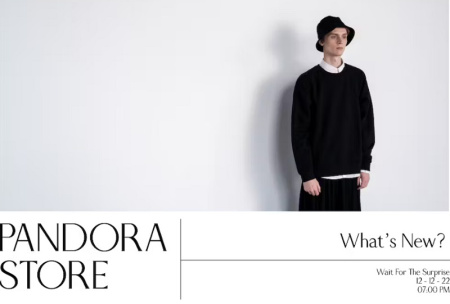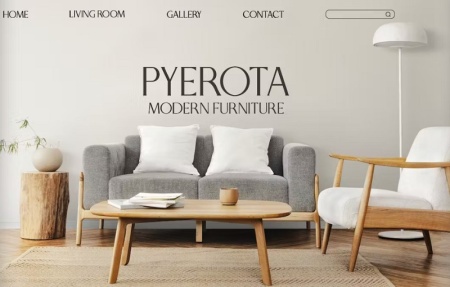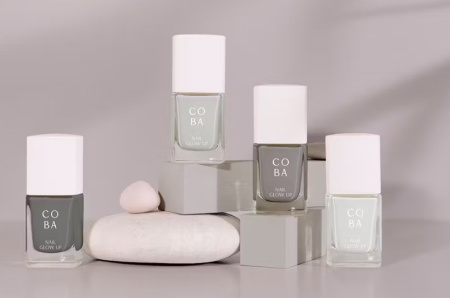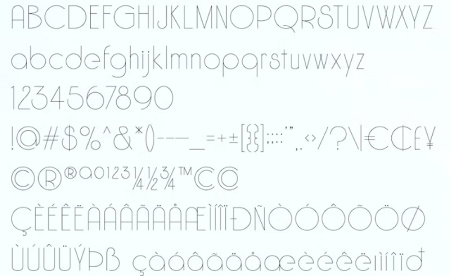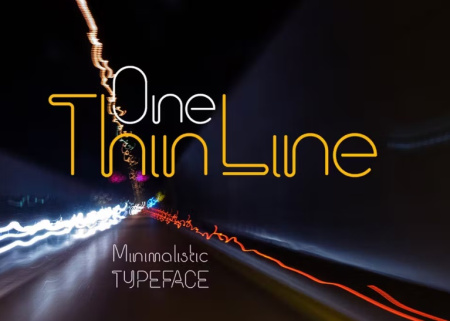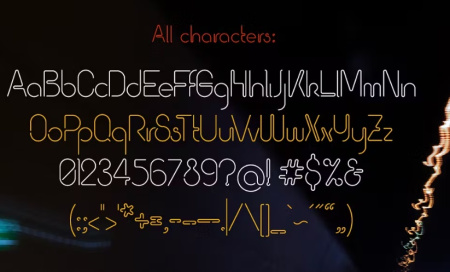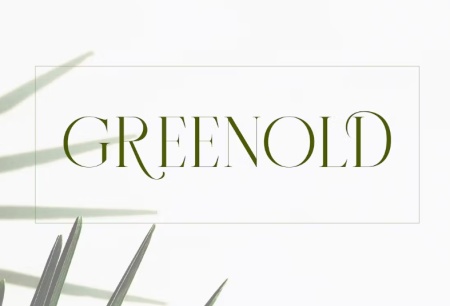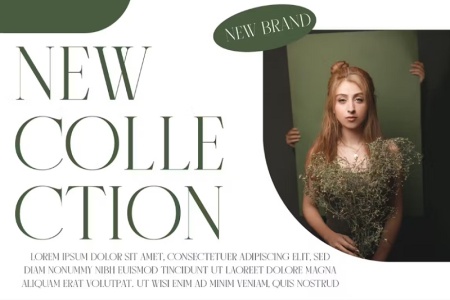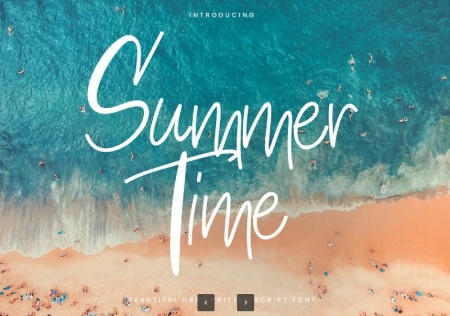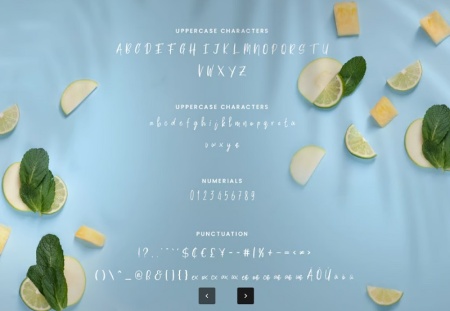
دانلود فونت باریک انگلیسی شامل مجموعه ای از فونت های زیبای انگلیسی با کاراکترهای ظریف و زیبا است. می توانید از فونت خط باریک انگلیسی در طرح های گرافیکی، مجلات، لوگوها، برندسازی هویت، برندهای مد و بسیاری موارد دیگر استفاده کنید. در ادامه با مشاهده تصاویر این فونت نازک و زیبای انگلیسی از سایت gfx با ما همراه باشید.
2- فونت خط باریک انگلیسی Sunday Shine
این فونت باریک هندسی کاملاً جدید و با سبک مدرن ارائه شده است. فونت خط باریک انگلیسی Sunday Shine مناسب برای شرکت ها، تجارت، تبلیغات، استفاده در فضای باز، دعوت نامه ها و موارد دیگر است. این فونت شامل فایل های ttfو otf می باشد.
3- فونت باریک و نازک انگلیسی Bepholar
در این قسمت با معرفی فونت باریک و نازک انگلیسی با نام Bepholar با طراحی مدرن و باریک با شما همراه هستیم. این فونت نازک انگلیسی برای هر پروژه ای مثل برندسازی، لوگو، چاپ تی شرت، محصول و بسیاری موارد دیگر مناسب است.
4- دانلود فونت انگلیسی باریک Fulgate Thin
در این بخش با معرفی یک فونت باریک انگلیسی با نام Fulgate Thin با شما همراه هستیم. این فونت زیبای باریک حس لوکس و زیبایی خاصی به راحی های شما می بخشد. این فونت باریک و نازک مناسب جهت استفاده در طرحهای گرافیکی و نرم افزارهای مختلف میباشد.
5- فونت انگلیسی نازک و باریک One Thin Line
این فونت انگلیسی نازک و باریک با نام One Thin Line مناسب برای تاپ متن مقاله، طراحی گرافیکی، تایپوگرافی، لوگو و برندینگ است. این فونت زیبا را به همراه مجموعه ای کامل از فونت های انگلیسی متنوع دیگر می توانید در ادامه دانلود نمایید.
6- فونت بسیار نازک و خطی انگلیسی
Modern Thin نام این فونت نازک و خطی انگلیسی است. شامل حروف بزرگ، حروف کوچک، عدد و نقطه گذاری ها می باشد. این فونت انگلیسی باریک با فایل های otf و ttf ارائه شده است.
7- فونت باریک انگلیسی برای اینشات
اگر به دنبال یک فونت باریک و نازک برای اینشات هستید، فونت باریک انگلیسی Summertime - Thin برای استفاده در تمام هدف های طراحی مناسب است. این فونت باریک و کشیده مناسب برای استفاده در کارت دعوت عروسی، طرح های تابستانی، کارت تبریک، پوستر، کارت پستال، عکاسی، برندسازی، سرمقاله و امضا می باشد.
دانلود فونت باریک و نازک انگلیسی برای طراحی های مدرن
اگر به دنبال دانلود فونت باریک برای طراحی های مدرن، مینیمال و حرفه ای هستید، مجموعه فونت های انگلیسی نازک می تواند انتخابی جذاب برای پروژه های گرافیکی شما باشد. استفاده از فونت انگلیسی نازک در طراحی لوگو، پوستر، کاور شبکه های اجتماعی، تبلیغات، بسته بندی و پروژه های تایپوگرافی، ظاهر کار را ظریف تر و امروزی تر نشان میدهد. در این مجموعه می توانید انواع فونت های Thin و Light انگلیسی را با طراحی های متنوع پیدا کنید و متناسب با سبک پروژه خود، فونت موردنظر را انتخاب و استفاده کنید.